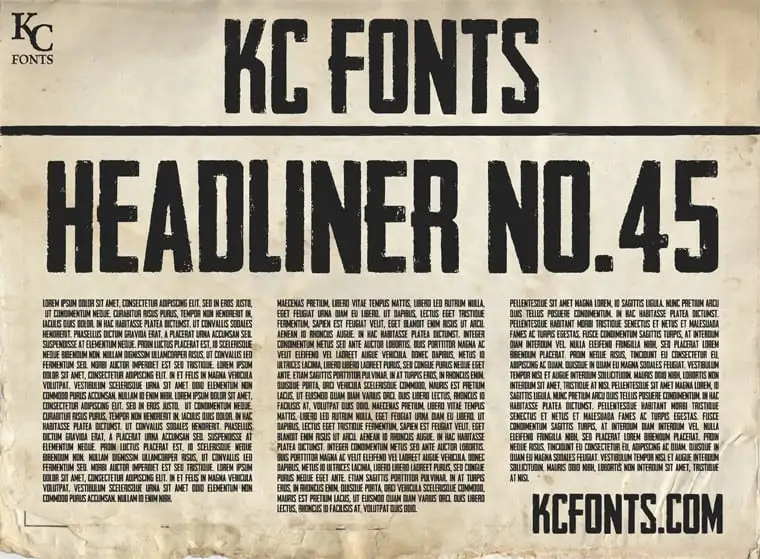
Headliner No. 45 Display Font – Download Grátis
A fonte ‘Headliner No. 45 Display Font’, criada pelo designer Hamilton, traz uma experiência visual única para projetos visuais que exigem atenção e destaque. Com linhas largas e bold, esta fonte é perfeita para headlines ou qualquer elemento de design que precise chamar a atenção imediatamente. Seu formato grande e claro permite que seja facilmente legível em grandes tamanhos, tornando-a uma escolha excelente para anúncios, headlines em blogs, ou até mesmo para uso em materiais impressos. A capacidade de alternar entre letras maiúsculas e minúsculas no próprio design da fonte oferece inúmeras possibilidades criativas na composição do layout. Seja você um designer gráfico buscando aperfeiçoar seu trabalho ou simplesmente alguém procurando por uma ferramenta para estilizar seus textos de maneira poderosa e moderna, ‘Headliner No. 45 Display Font’ é uma fonte que não deixará você insatisfeito.